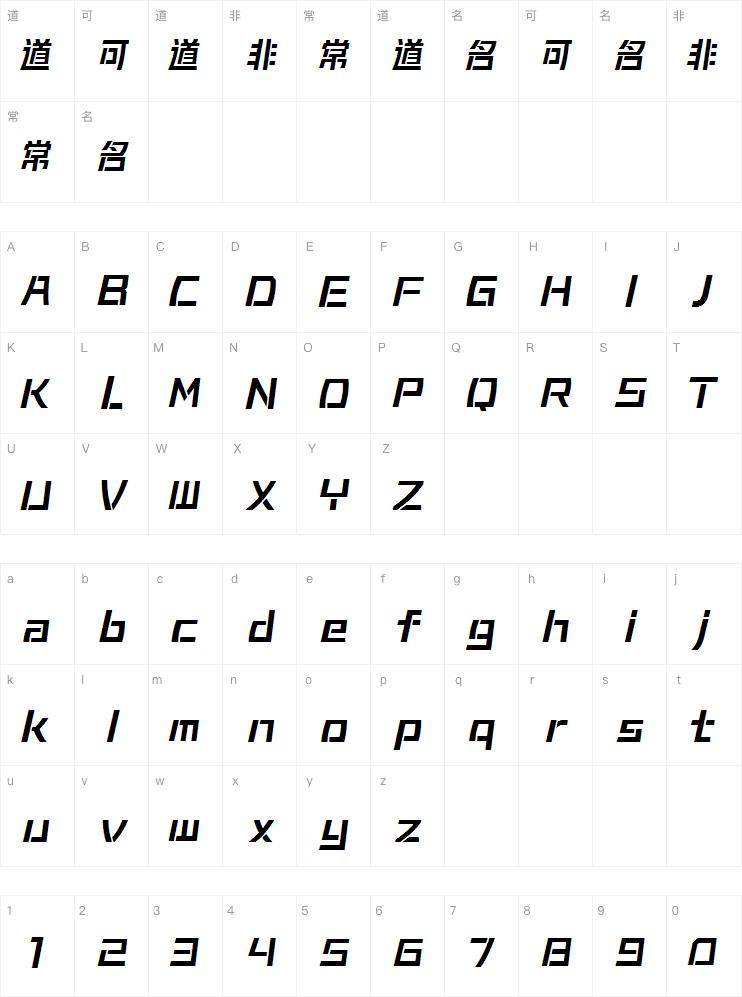
锐字奥运精神揽金摘银家族是一款简洁大气的黑体创意字。其作为斜体字创新性的做出左侧单边斜度的设计,整体比例偏高中宫饱满 ,稳定大气有间距动态感,笔画连接处的切割增强了整体的动感,更适合用于运动比赛的场景。适合于文化宣传、电商设计、体育海报、LOGO等场景
锐字奥运精神揽金摘银-闪 超黑
锐字奥运精神揽金摘银-闪 大黑